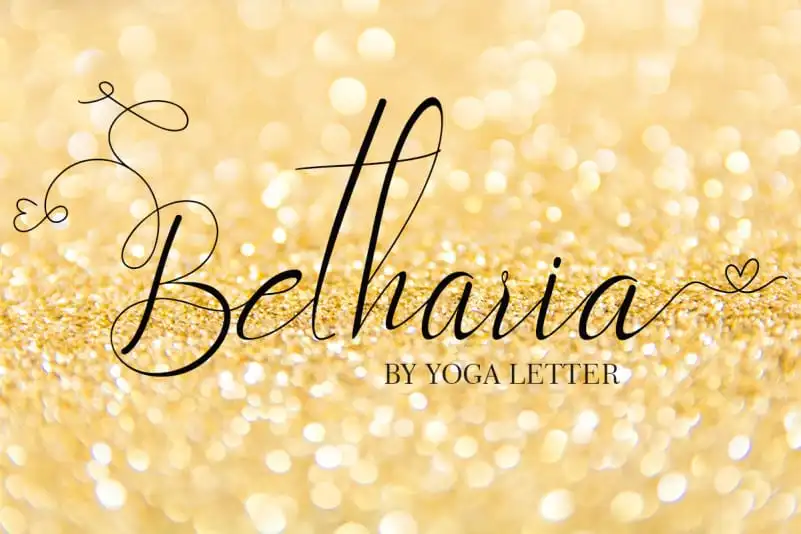
Betharia Calligraphy Font é uma fonte criada a partir de letras escritas a mão moderna. Ela transmite beleza e elegância com amor, tornando-a perfeita para trabalhos artísticos. Além de ser elegante e bonito, Betharia também possui um toque singular que pode dar mais vida ao seu projeto. Suas linhas fluidas são ideais para designs como casamentos, desde criação de marca até cartazes promocionais e mensagens nas redes sociais. Perfecta para tornar seus momentos de viagem ainda mais agradáveis, é uma escolha perfeita para adicionar o toque final em suas publicações no Instagram ou outras mídias sociais. Esta fonte é versátil e adequada para várias aplicações gráficas.